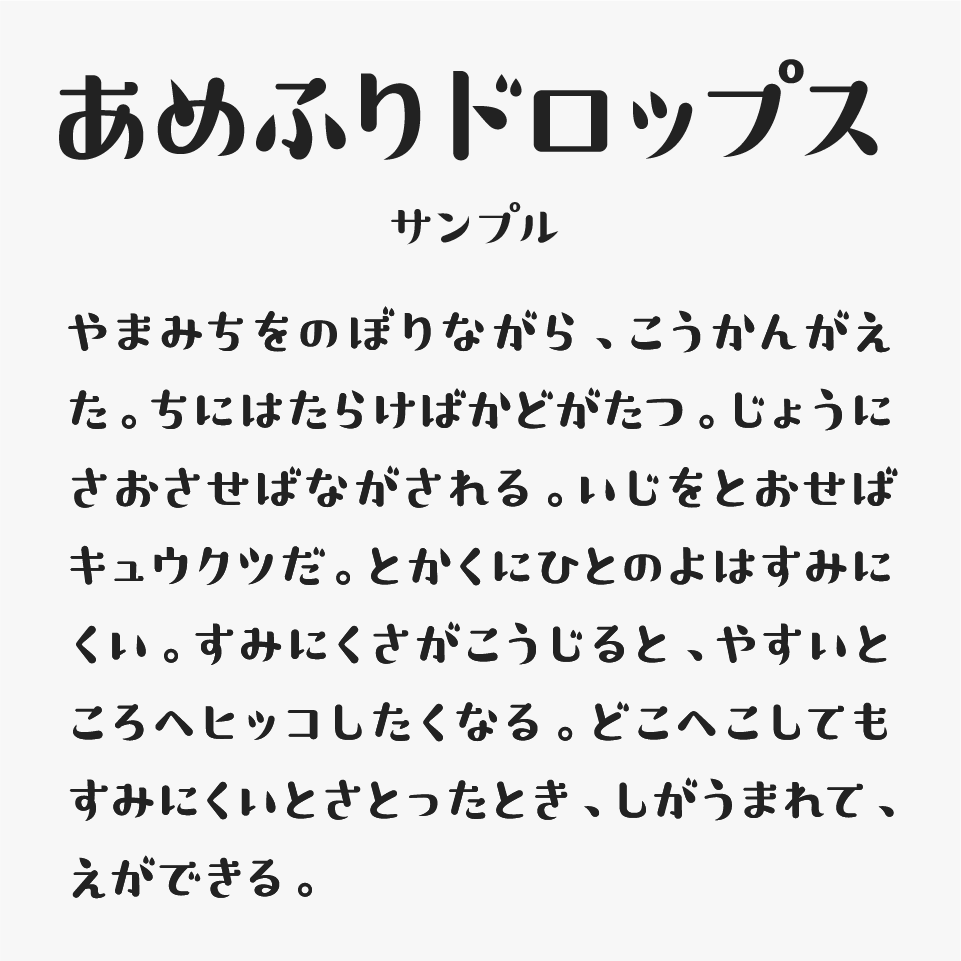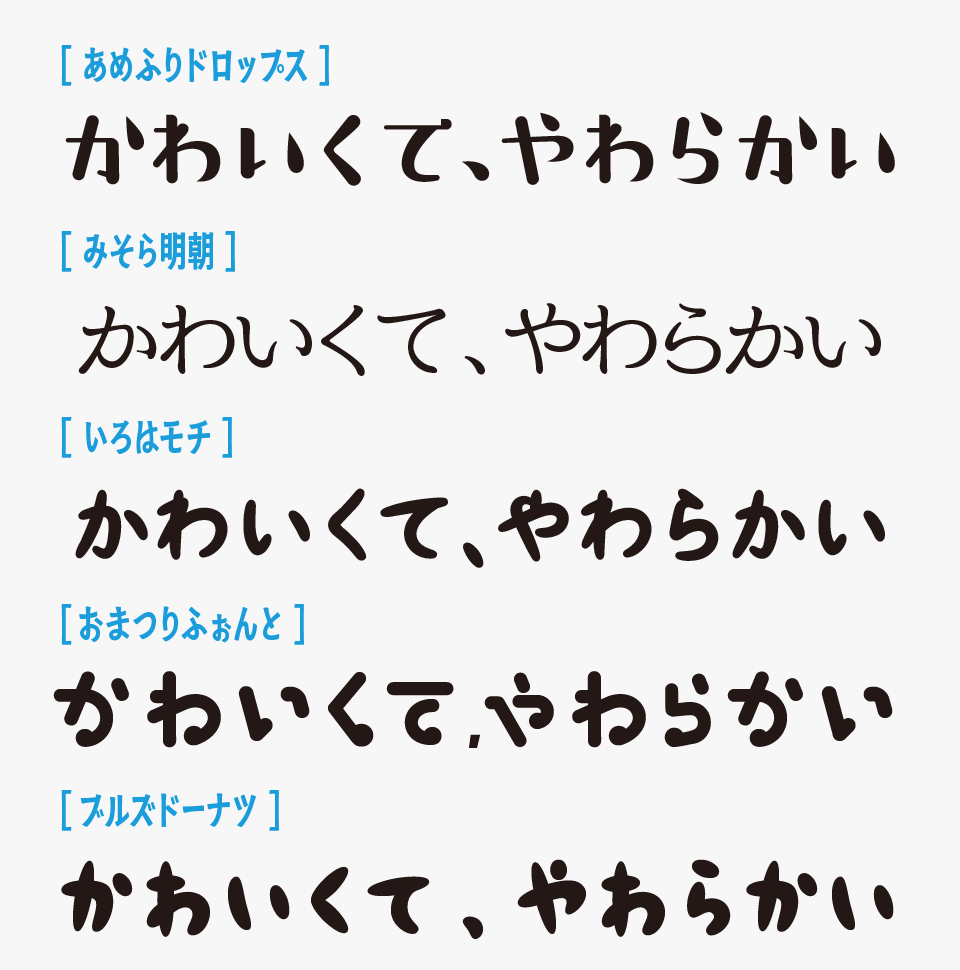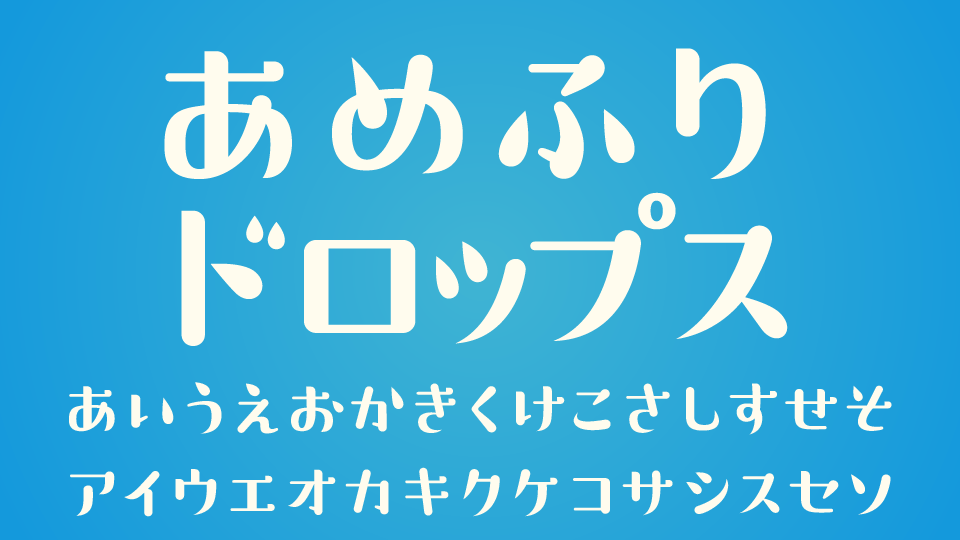
あめふりドロップスフォントは、水滴がぽたっと落ちる瞬間を切り取ったような、遊び心のあるフォルムがかわいらしいデザインフォントです。
丸みを帯びたやわらかなフォルムをベースにしながら、文字の一部にしずくを思わせる装飾が加えられており、かわいらしさと個性をバランスよく両立しています。ポップな雰囲気の中にも爽やかさや透明感があり、見ていて楽しくなるフォントです。
水滴のモチーフが、親しみやすく印象に残るデザインを作りやすく、SNS投稿やYouTubeサムネイル、季節イベントのバナー、子ども向けコンテンツ、ポップなロゴ制作などにぴったりなフォントです。特に梅雨や夏をテーマにしたデザインとも相性がよく、明るく楽しい世界観を表現したい場面で活躍するフォントです。
あめふりドロップスフォントを、丸みのある可愛らしいフォントと比較してみると、やさしくふんわりとした雰囲気の中にある“素朴さ”と“透明感”が特に魅力のフォントです。
比較フォントは、「みそら明朝」「いろはモチ」「おまつりふぉんと」「ブルズドーナツ」と使用していますが、どのフォントも見ているだけで穏やかでやさしい気持ちになれるようなフォントなので、ぜひあわせてチェックしてみてください。